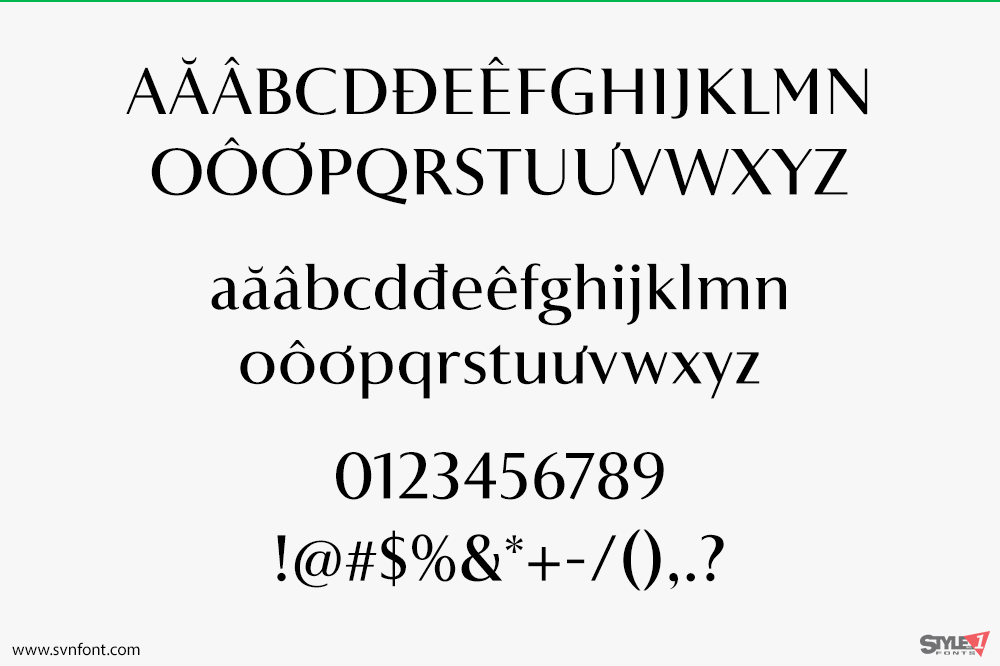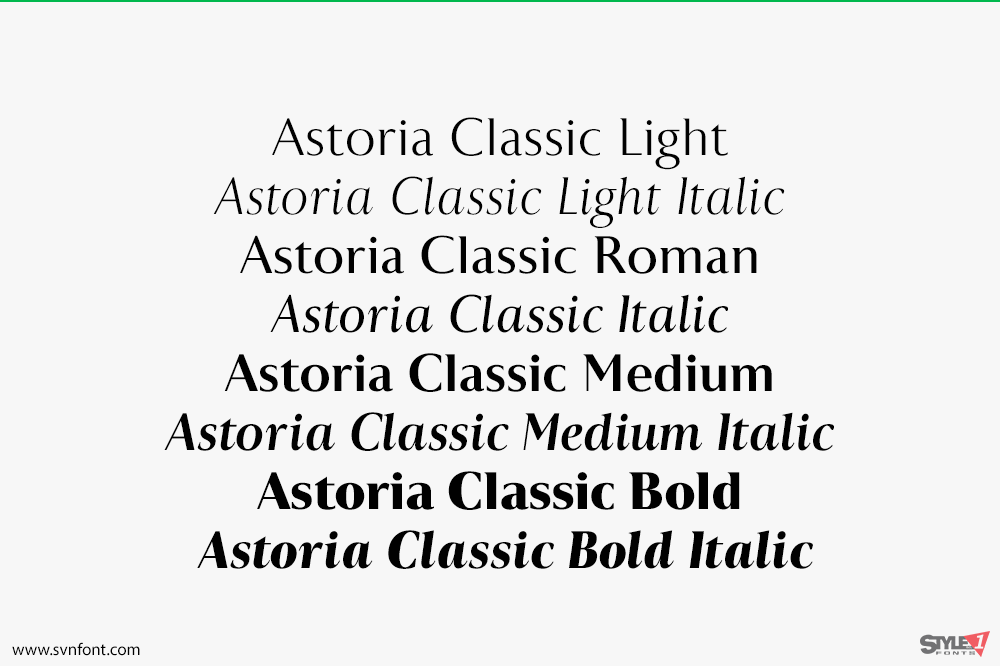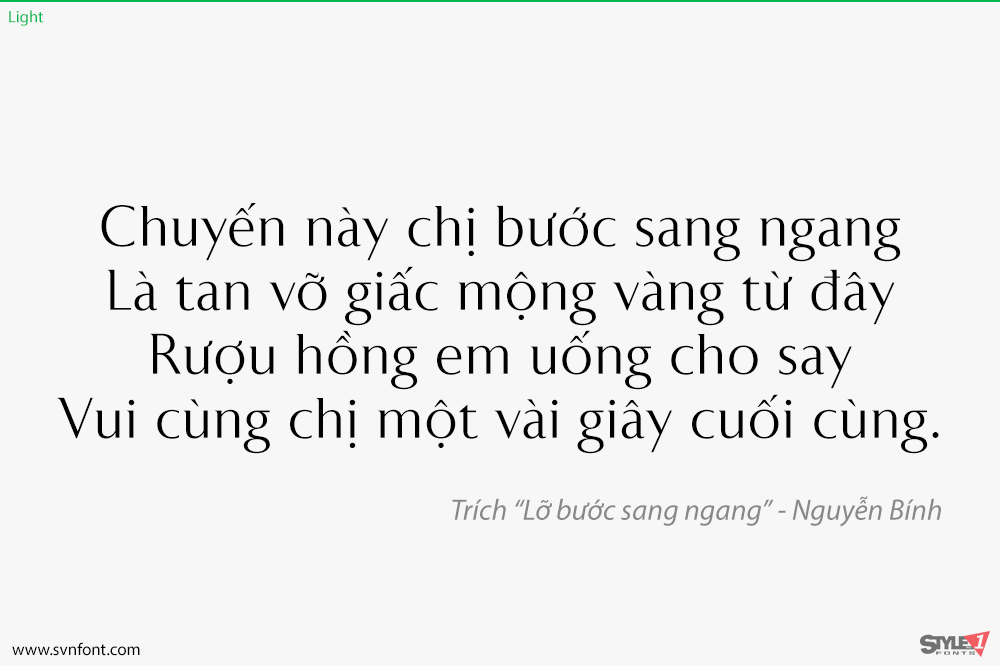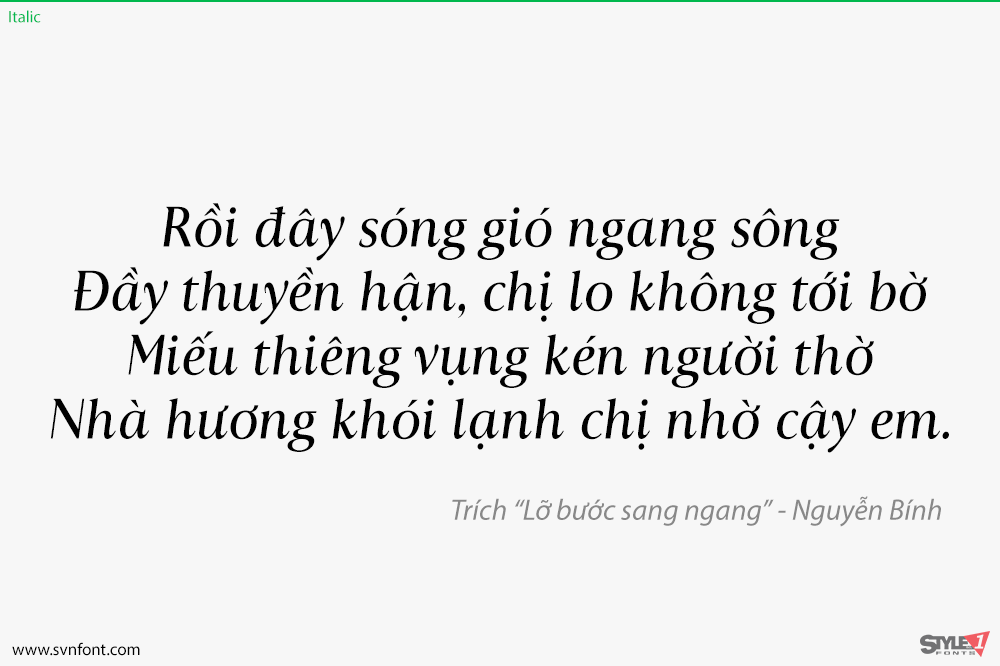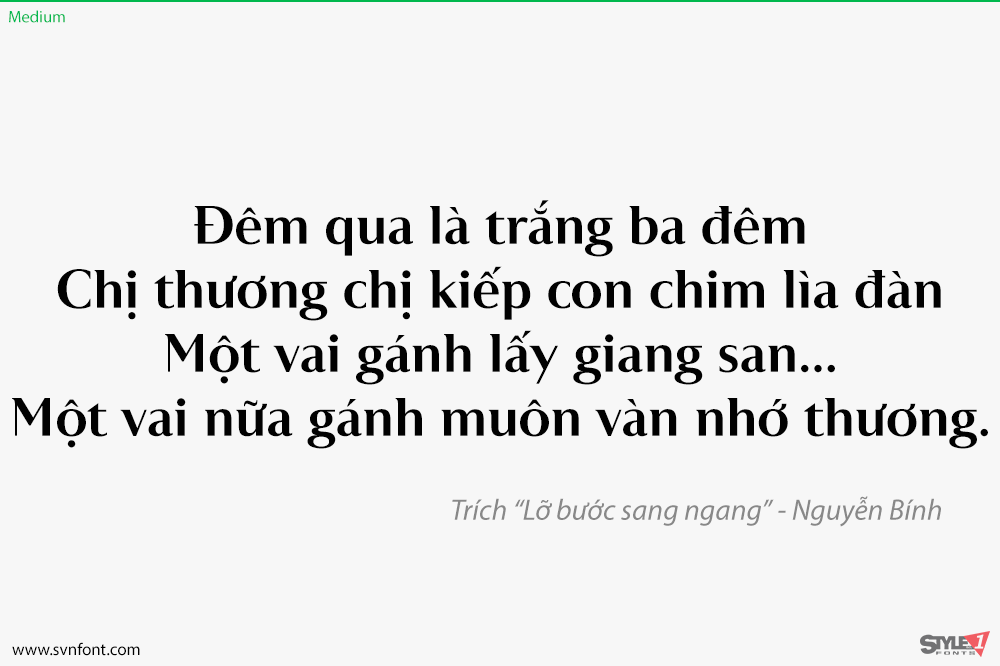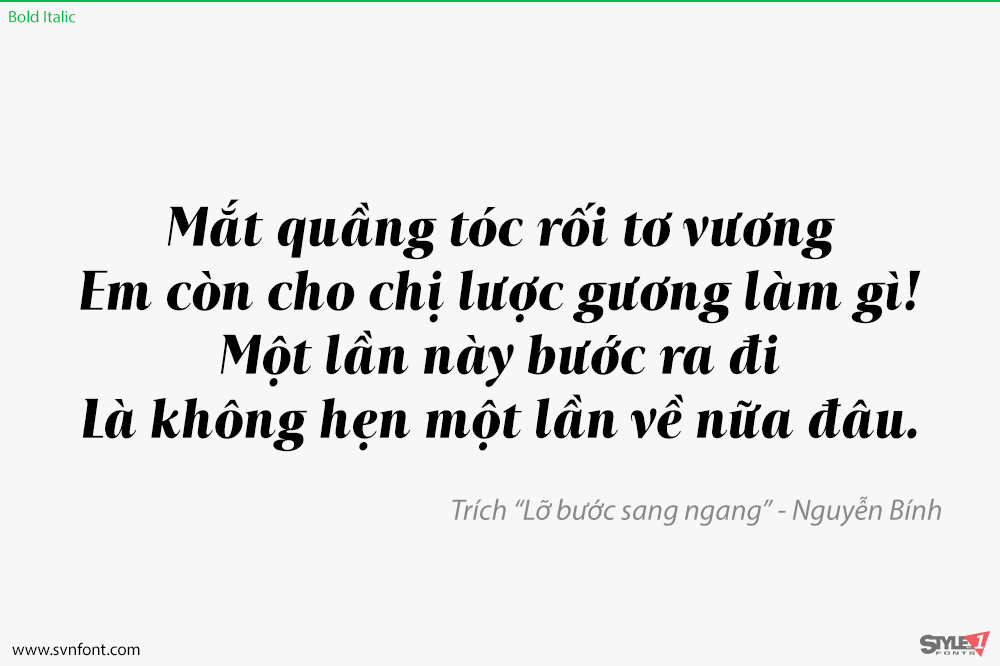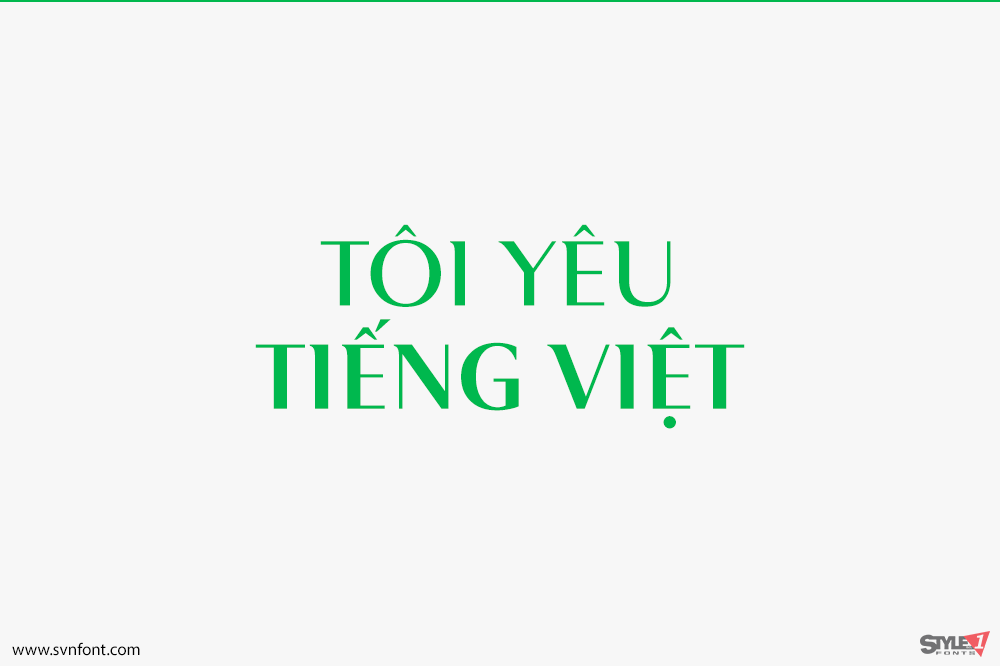
Thành viên mới nhất trong bộ Astoria, Astoria Classic có cùng những đặc điểm cơ bản như Astoria nhưng với ứng suất dọc (vertical stress). Nét serif tinh tế ở phía trên bên trái đặc trưng, khiến nó không hoàn toàn là Roman và cũng không hoàn toàn là sans, đã được giữ lại. Không giống như Astoria, các kiểu chữ nghiêng (Italics) về hình thức mang phong cách cổ điển nhưng lại có vẻ ngoài hiện đại. Kiểu chữ này được thiết kế đặc biệt để làm font chữ nội dung (text face), tuy nhiên nó vẫn hoạt động rất tốt như một font tiêu đề.
Nhà thiết kế: Alan Meeks
Nhà phát hành: Alan Meeks